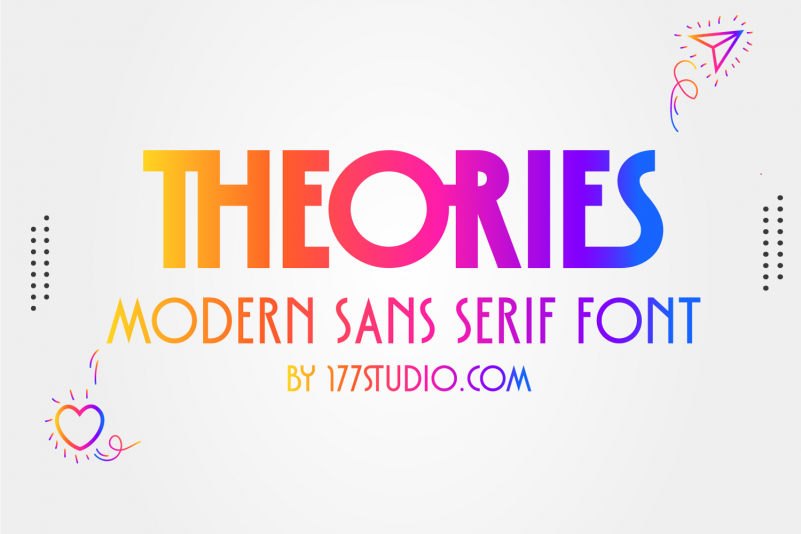
A fonte Theories é uma elegante e moderna sans serif, projetada para atender a um leque amplo de usos. Combinando perfeitamente estilos antigos e novos, essa fonte abrange versatilidade e clareza em diversos tamanhos. Ideal tanto para projetos de marca como criação de logotipos, design de roupas, embalagens de produtos, cabeçalhos de revistas ou até mesmo textos decorativos sobre fundo de imagem, Theories é uma escolha perfeita para qualquer aplicação visual onde um estilo contemporâneo e sofisticado seja desejável. Com a 177Studio como designer, Theories oferece uma variedade impressionante de opções, garantindo que seja compatível com todas as necessidades do seu projeto.